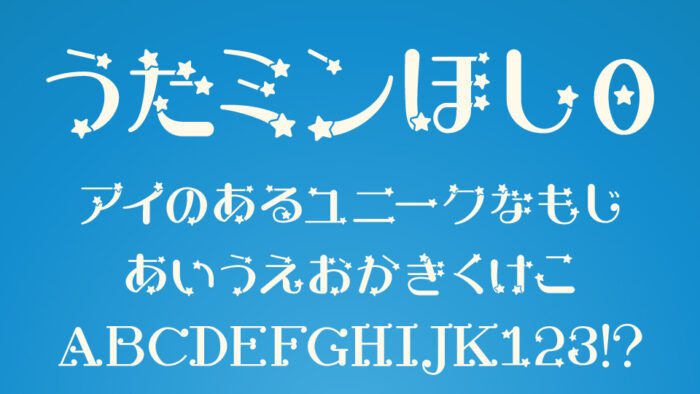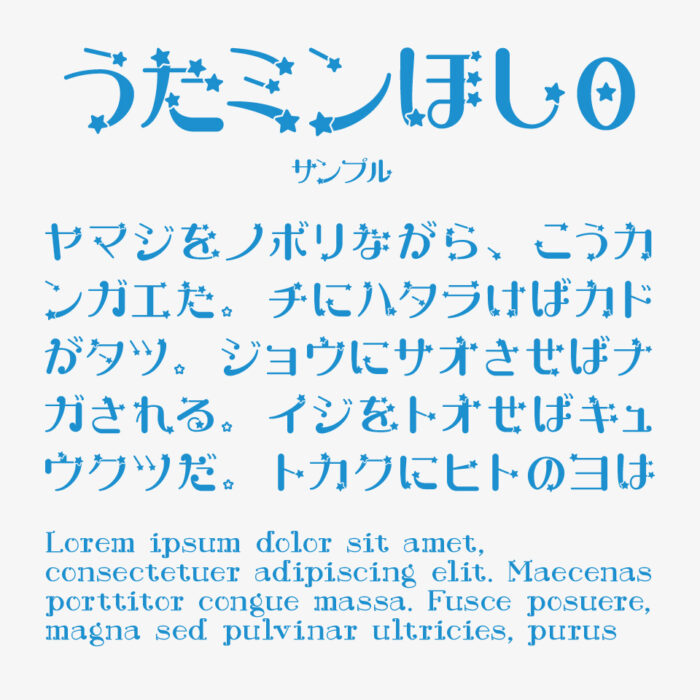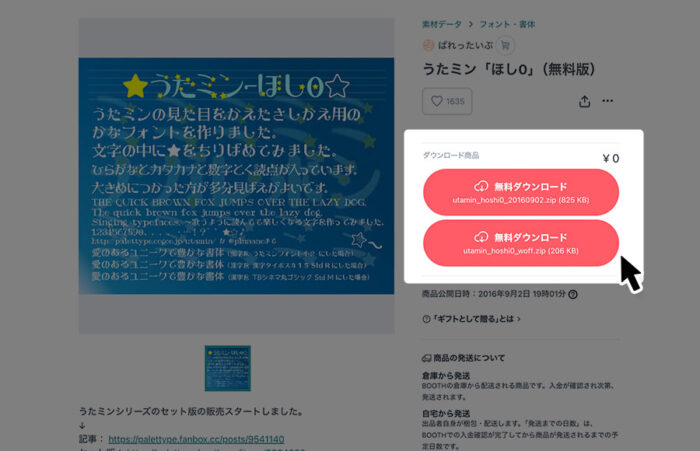
うたミンぼし0フォントは、文字の中に星が散りばめられたユニークでポップなデザインフォントです。
丸ゴシック系の骨格に、星モチーフをアクセントとして散りばめられていて、遊び心が詰まっている個性的なフォントです。
キラキラしたモチーフを活かし、アイドル関連のデザインや推し活グッズにぴったりのフォントです。
うたミン「ほし0」